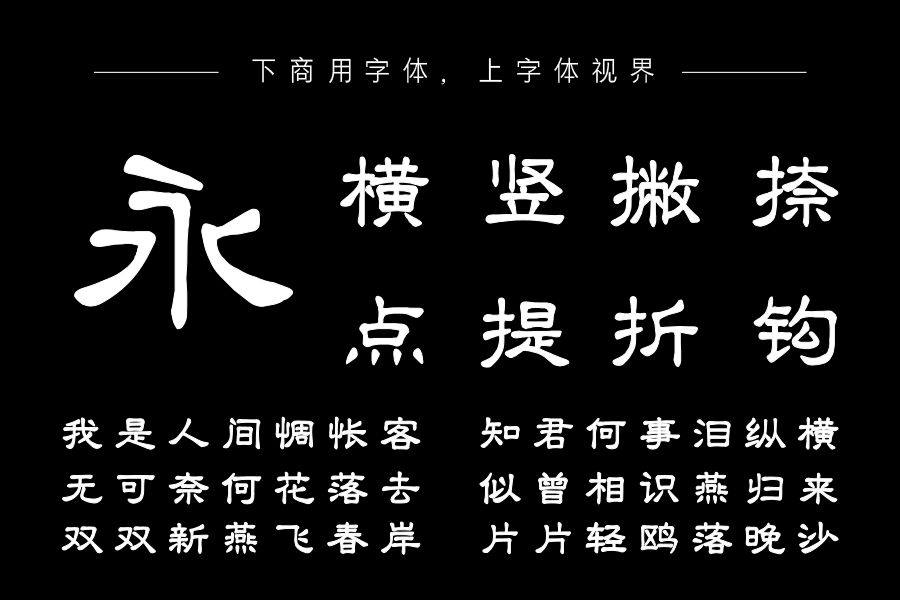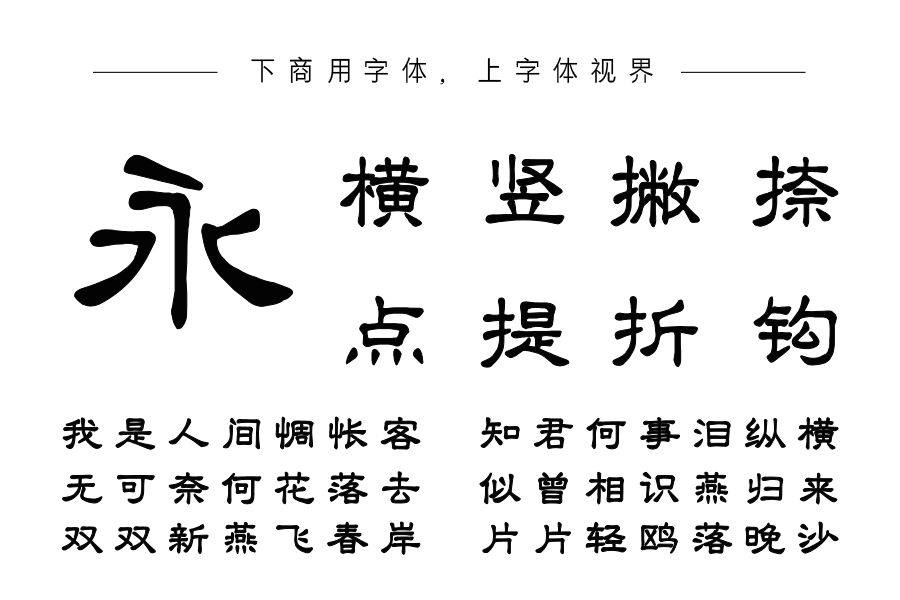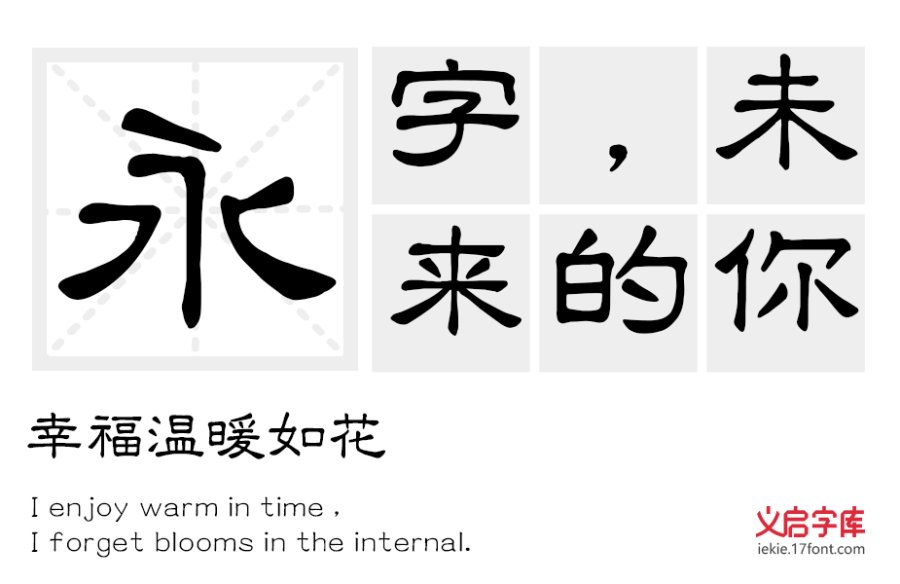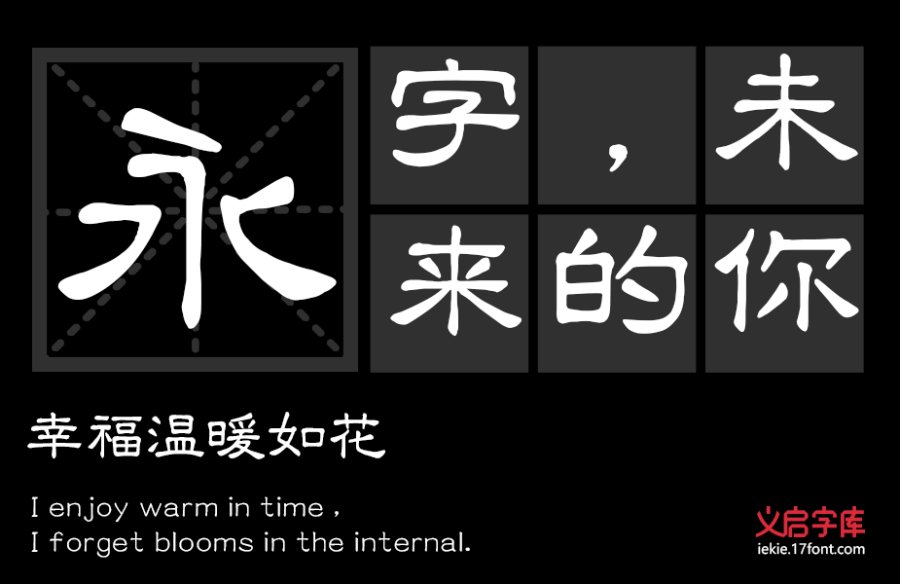
隶书,亦称汉隶,是汉字中常见的一种庄重的字体,书写效果略微宽扁,横画长而直画短,呈长方形状,讲究“蚕头雁尾”、“一波三折”。隶书起源于秦朝,由程邈形理而成,在东汉时期达到顶峰,书法界有“汉隶唐楷”之称。 义启隶书体,笔画上保留深化了波折的元素,由于考虑到整体的可塑性,起收处弱化方笔加强圆笔画,所谓蚕头雁尾修饰弱化些。结构内放外收,整体呈扁方形,重心在一条轴线上。章法,左右波折遥相呼应,气息通畅一气呵成。分享到